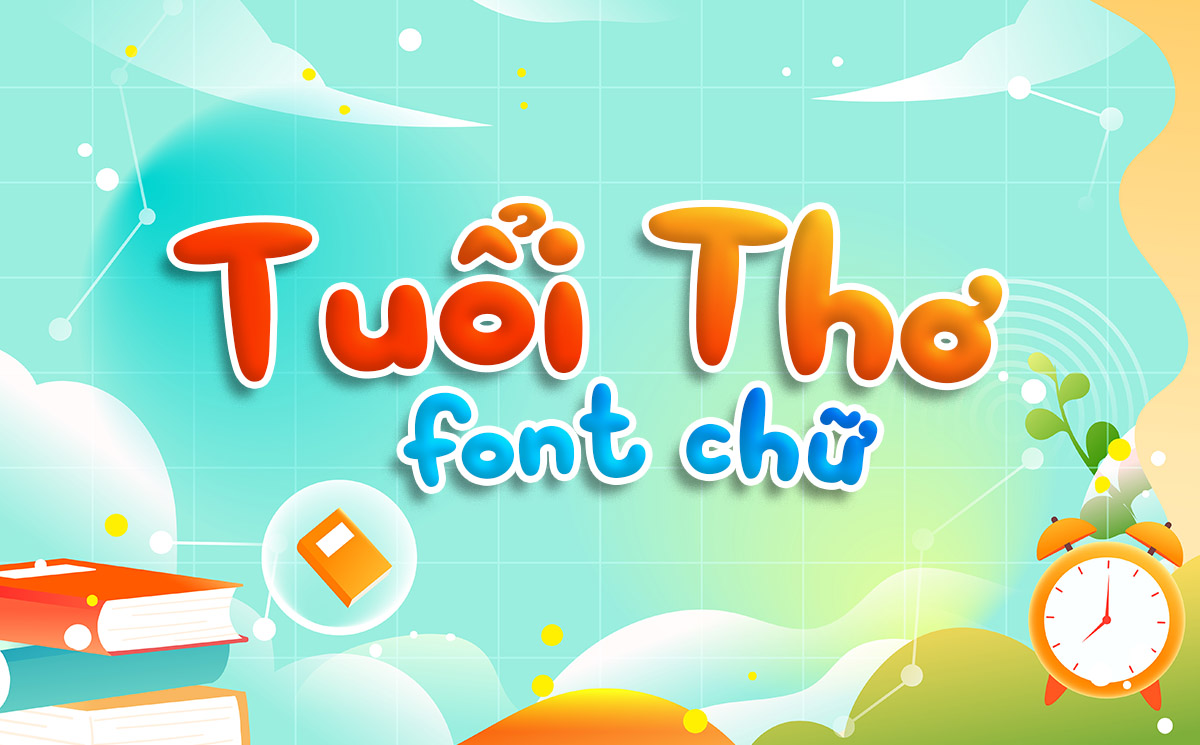
Font chữ hoạt hình bong bóng SVN-Bublont Việt Hóa
Nếu bạn đang tìm kiếm một làn gió mới tràn đầy năng lượng tươi trẻ và sự ngộ nghĩnh cho các dự án sáng tạo của mình, Font chữ hoạt hình bong bóng SVN-Bublont Việt Hóa chính là sự lựa chọn không thể hoàn hảo hơn. Đây là bộ font được thiết kế với phong cách bong bóng bo tròn độc đáo, mang lại cảm giác thân thiện, vui nhộn và cực kỳ thu hút thị giác người xem ngay từ ánh nhìn đầu tiên. Được Việt hóa tỉ mỉ bởi đội ngũ SVN, font chữ này hỗ trợ đầy đủ bộ ký tự tiếng Việt có dấu, giúp các designer dễ dàng hiện thực hóa mọi ý tưởng thiết kế độc đáo mà không lo lỗi font.</p>
Khám Phá Font Chữ Hoạt Hình Bong Bóng SVN-Bublont Việt Hóa – Giải Pháp Thiết Kế Vui Nhộn Và Độc Đáo
Trong thế giới thiết kế đồ họa hiện đại, typography đóng một vai trò vô cùng quan trọng trong việc truyền tải thông điệp và cảm xúc của sản phẩm. Một font chữ phù hợp không chỉ giúp bài viết dễ đọc mà còn tạo nên bản sắc thương hiệu và ghi dấu ấn đậm nét trong lòng khách hàng. Đặc biệt là đối với các dự án hướng tới đối tượng trẻ em, giới trẻ hoặc các chủ đề mang tính giải trí, sự xuất hiện của những font chữ nét dày, uốn lượn phồng to như chiếc bong bóng luôn tạo ra sức hút khó cưỡng.
Font chữ hoạt hình bong bóng SVN-Bublont Việt Hóa ra đời để đáp ứng chính xác nhu cầu đó. Kết hợp hoàn hảo giữa nét vẽ tay mượt mà, cấu trúc hình khối bong bóng căng tròn và đường nét tươi tắn, SVN-Bublont truyền tải trọn vẹn sự tinh nghịch, đáng yêu và đầy sức sống. Cho dù bạn đang thiết kế bìa sách truyện tranh, ấn phẩm quảng cáo cho khu vui chơi, banner khuyến mãi đồ chơi hay làm video clip hoạt hình trên YouTube, SVN-Bublont đều thể hiện xuất sắc vai trò của một giải pháp typography chuyên nghiệp và bắt mắt.
1. Nét Chữ Bong Bóng Uốn Lượn Đầy Sáng Tạo Vui Nhộn
Điểm đặc trưng nổi bật nhất của font chữ hoạt hình bong bóng SVN-Bublont Việt Hóa chính là tạo hình độc đáo mô phỏng những quả bong bóng căng tròn, mềm mại. Các đường nét của chữ được bo tròn tuyệt đối ở các góc, loại bỏ hoàn toàn cảm giác thô cứng hay sắc nhọn thường thấy ở các font chữ truyền thống. Độ dày của các nét chữ được phân bổ linh hoạt, tạo nên hiệu ứng thị giác dạng khối nổi tự nhiên, giúp từ ngữ như đang vươn lên và nổi bật hẳn so với phông nền thiết kế.
Sự vui nhộn trong từng nét chữ SVN-Bublont mang lại bầu không khí vô cùng thư giãn và tràn đầy năng lượng tích cực. Điều này đặc biệt phù hợp để truyền tải các thông điệp mang tính giải trí, thân thiện và giàu tính sáng tạo. Khi phối hợp cùng các bảng màu sắc tươi sáng như vàng, cam, hồng, xanh lá cây hay xanh dương, bộ font chữ này sẽ ngay lập tức biến bức ảnh hay banner thiết kế của bạn trở thành một tác phẩm nghệ thuật bắt mắt và giàu cảm xúc.
2. Hỗ Trợ Tiếng Việt Đầy Đủ Với Bộ Ký Tự Chuẩn SVN
Một trong những rào cản lớn nhất khi các designer Việt Nam sử dụng các font chữ hoạt hình nước ngoài là vấn đề thiếu dấu hoặc bị lỗi hiển thị các ký tự tiếng Việt như ă, â, đ, ê, ô, ơ, ư cũng như các dấu thanh (huyền, sắc, hỏi, ngã, nặng). Nhận thức được khó khăn đó, phiên bản SVN-Bublont Việt Hóa đã được chỉnh sửa và tối ưu hóa tỉ mỉ từng chi tiết ký tự tiếng Việt, bảo đảm tính thẩm mỹ đồng nhất toàn diện.
Tất cả các dấu tiếng Việt trong SVN-Bublont đều được vẽ lại thủ công sao cho hòa hợp hoàn hảo với độ phồng tròn của thân chữ chính. Khoảng cách giữa các ký tự và độ cao dòng cũng được tinh chỉnh cẩn thận, tránh hiện tượng các dấu thanh bị đè lên chữ hoặc bị trôi quá xa gây mất cân đối. Nhờ vậy, bạn có thể tự tin gõ các đoạn văn bản tiếng Việt dài hay các câu slogan ngắn mà vẫn đảm bảo độ hiển thị nét căng, chuẩn xác và cực kỳ thẩm mỹ trên mọi thiết bị.</p>
3. Tính Ứng Dụng Đa Dạng Cho Nhiều Loại Hình Thiết Kế
Khả năng biến hóa linh hoạt là một ưu điểm vượt trội giúp SVN-Bublont Việt Hóa trở thành font chữ được yêu thích trong bộ sưu tập của nhiều nhà thiết kế đồ họa. Không bị giới hạn trong một khuôn khổ nhất định, bộ font này có thể ứng dụng đa dạng vào vô số lĩnh vực thiết kế khác nhau:
• Ấn phẩm cho trẻ em: Bìa sách truyện tranh, sách tô màu, dụng cụ học tập, đồ chơi thông minh và biển hiệu trường mầm non.
• Ngành thực phẩm và F&B: Bao bì bánh kẹo, nhãn dán kem, menu quán trà sữa, thương hiệu đồ ăn vặt và các chương trình khuyến mãi mua sắm.
• Thiết kế truyền thông kỹ thuật số: Cover Facebook, thumbnail video YouTube dành cho thiếu nhi, hình ảnh chạy quảng cáo Instagram, banner sự kiện sinh nhật, Tết Trung Thu, Quốc tế Thiếu nhi.
• Thời trang đồ họa: In ấn áo phông hoạt hình, túi vải canvas, phụ kiện thời trang đường phố mang phong cách đáng yêu, năng động.
Font chữ Bublont là một font chữ khá sáng tạo và cute, được thiết kế bởi Mans Greback. Font chữ này có thể áp dụng vào thiết kế cho nhiều các ấn phẩm khác nhau như poster, banner…
Bublont có tổng thể được thiết kế với các đường nét tròn trịa, mềm mại mảng tới cảm giác vui tươi, mang tới một sự khác biệt so với các font chữ khác. Các ký tự trong font chữ đều được tác giả thiết kế khá tỉ mỉ để đảm bảo tính nhất quán. Font chữ Bublont được Việt hóa bởi SVN, đã được bổ sung thêm đầy đủ các dấu và ký tự tiếng Việt, mang tới sự tiện lợi và tiết kiệm thời gian khi sử dụng tiếng Việt.